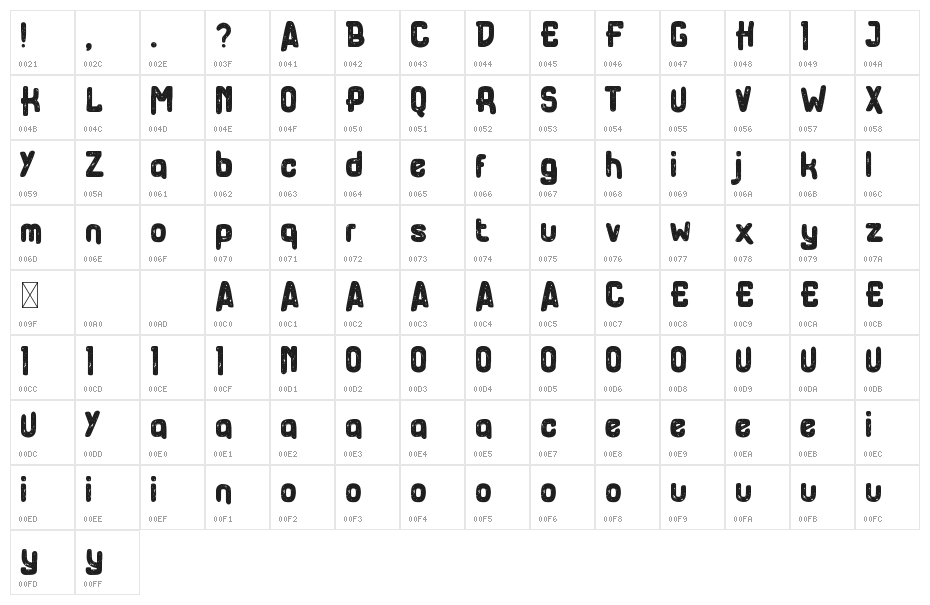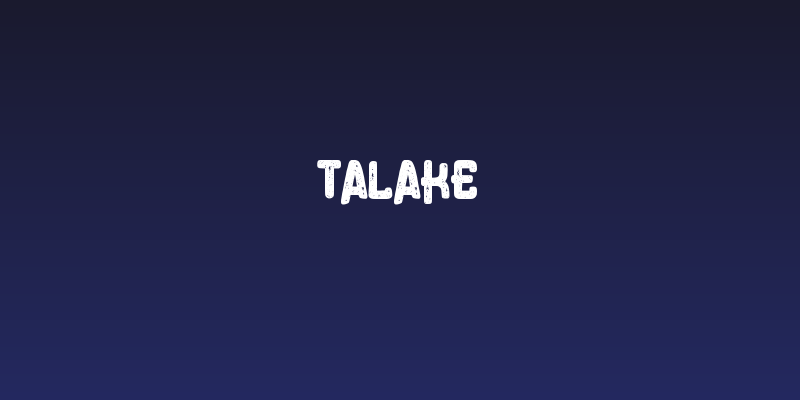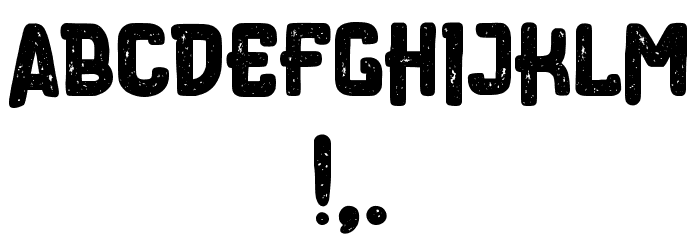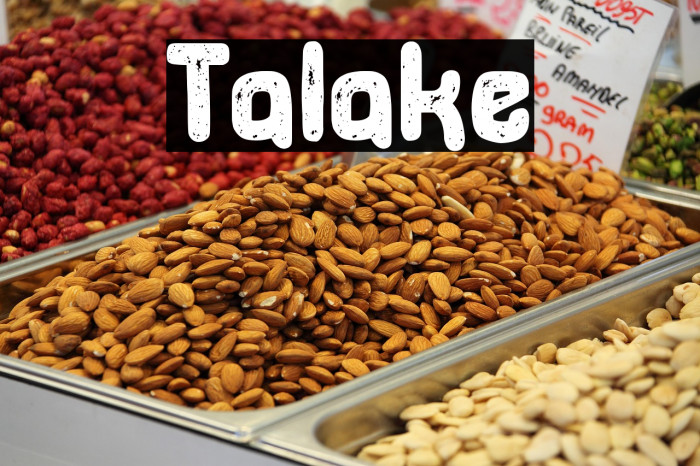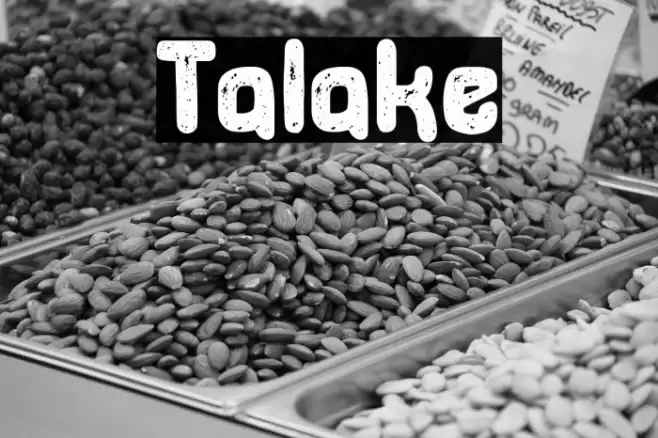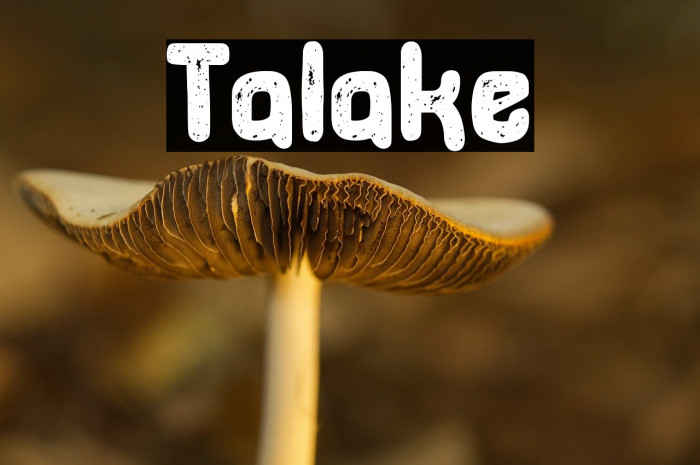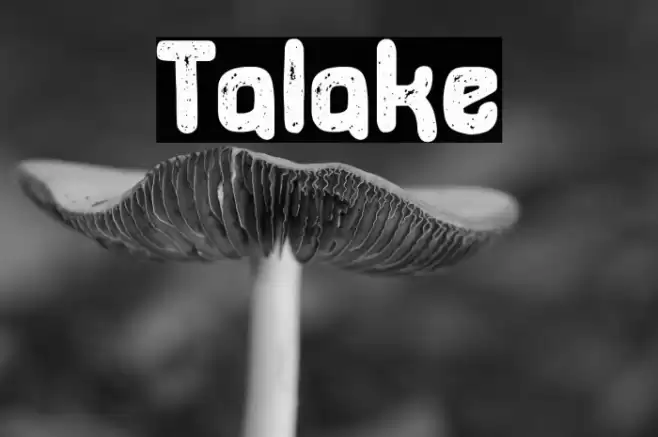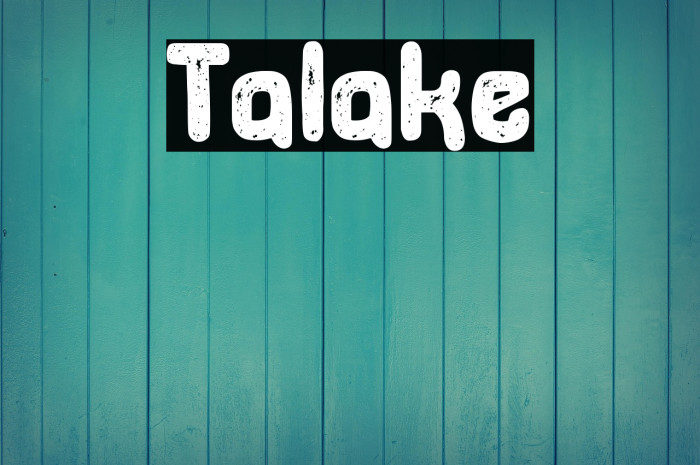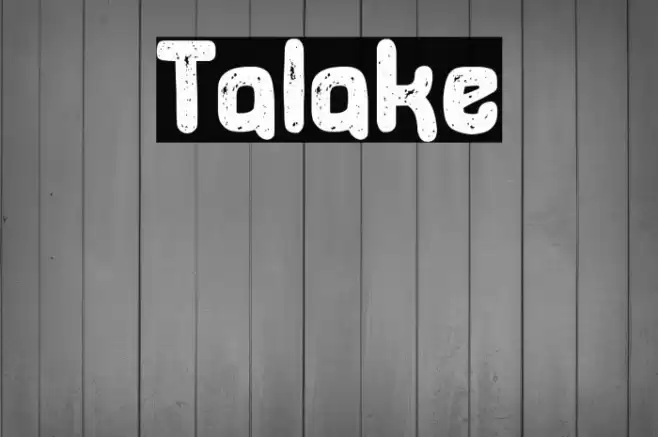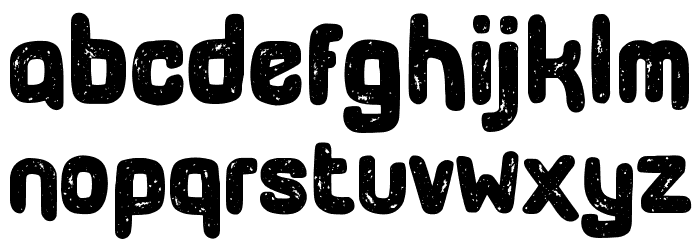
Talake Font
| النمط العام | Vintage |
| حالة الاستخدام | Logos, Posters, Headlines |
| مشاريع مقترحة | Ideal for vintage posters, retro-themed branding, t-shirt designs, and creative packaging. |